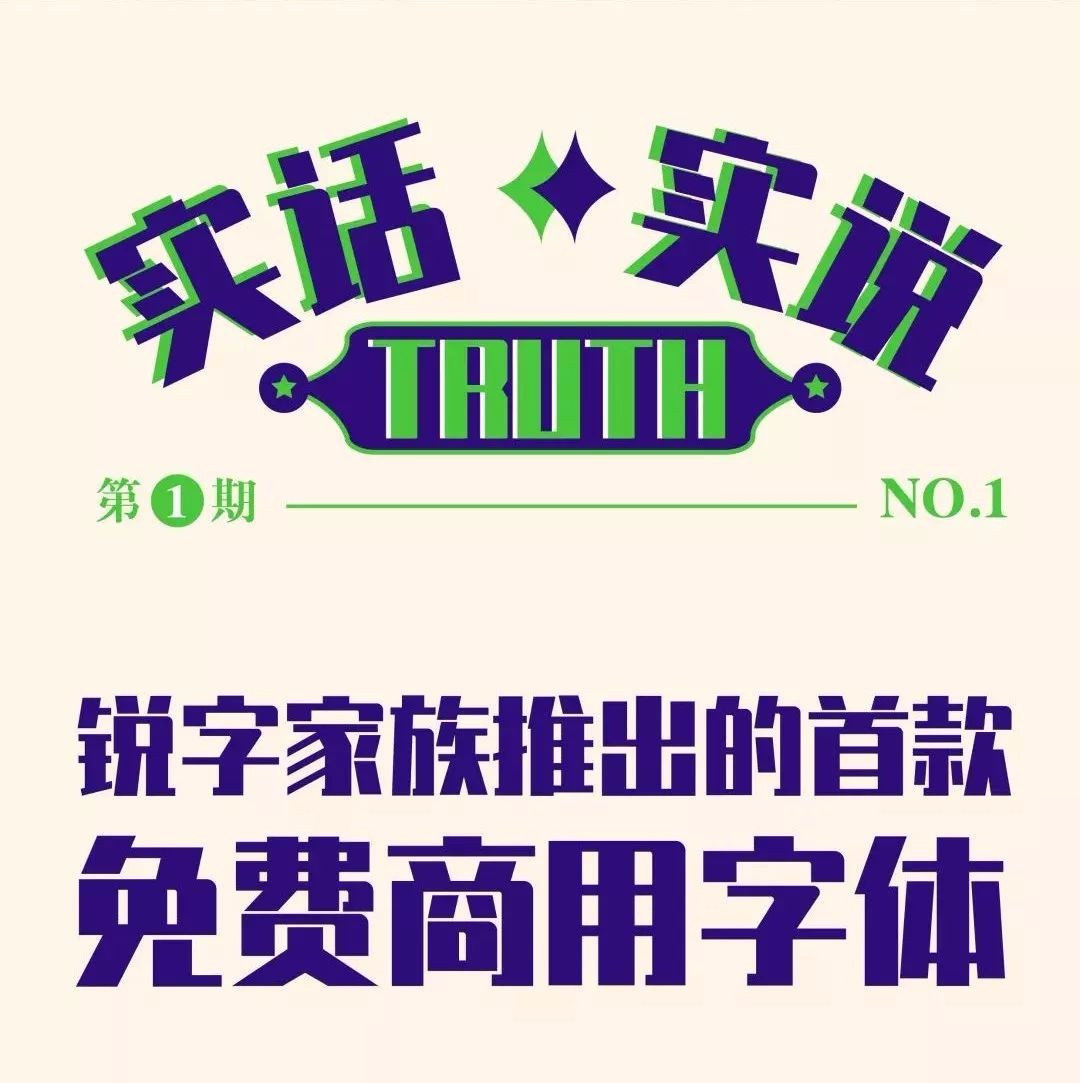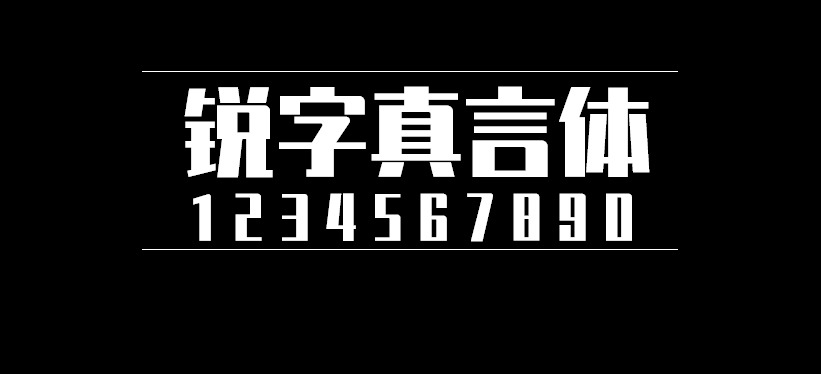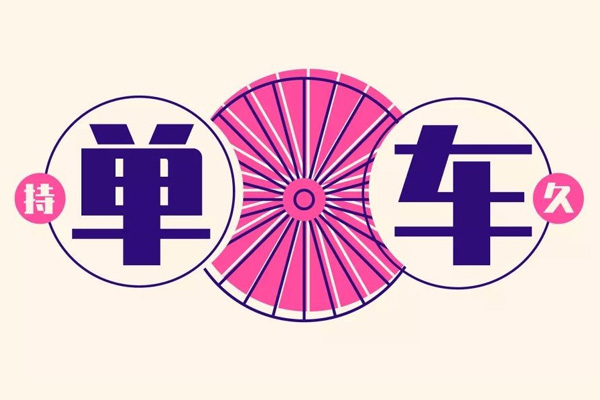
锐字真言体
锐字真言体是由国内新锐字库公司——锐字字库,于2018年10月17日发布的。值得一提的是,这款字体完全免费商用,这也是锐字家族首款免费商用字体。
锐字真言体笔触浑厚有力,笔画曲折有度,字形个性鲜明,刚柔并济,落笔简洁有序,给人以遒劲有力、端正凝练的感受。 直角与圆角的错落搭配使得字体婉转有度,落落大方,具有自己独到的风格! 这款字体特别适用于文字标题、竞技视觉、广告设计、个性品牌设计推广、企业宣传及时尚品牌的设计应用。 锐字家族是一家成立不久的字体公司,专注提供字体产品和解决方案,涵闸创意汉字字体设计、汉字字库制作等服务。
目前锐字家族已发布了十余款字库,锐字真言体是其中唯一一款免费商用字体。
锐字真言体字体效果预览